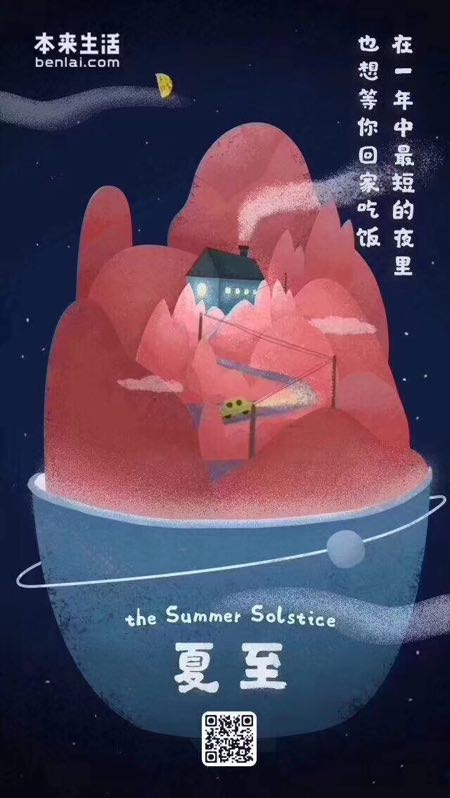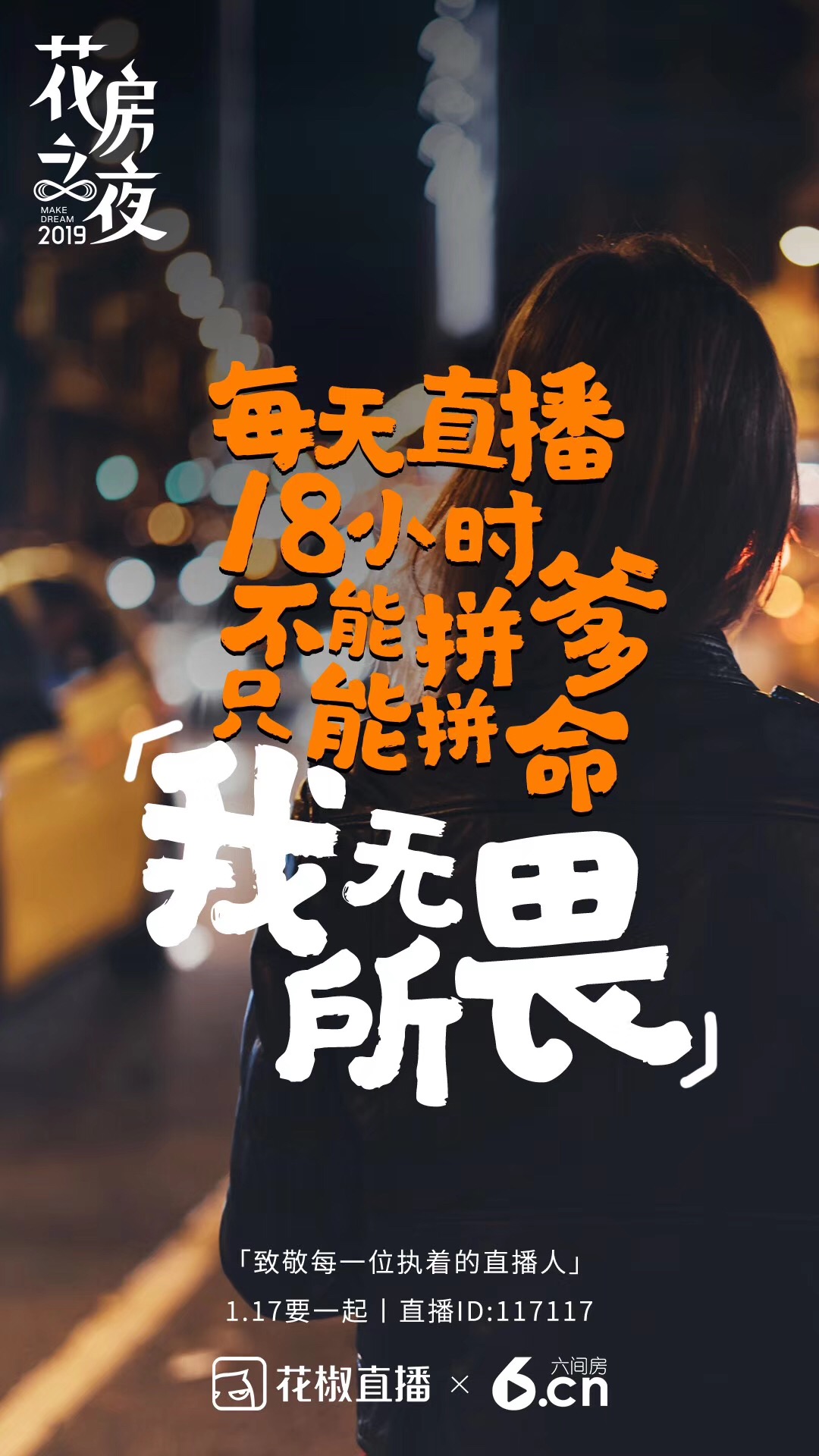
方正字迹-新手书
范雅琼
隶书、创意书写
2015
新手书是一款带有书法味道的纯手写字体,将隶书与楷书笔画相结合,字型偏方,笔画中也减少了过多的处理和笔势,厚重、饱满。因为是纯手写的原因,它独特的气质更与其他字体不同,看似统一,其实各有各的味道,每个字都可以独具风情。字由字在,大到自然,便是对它最好的诠释。